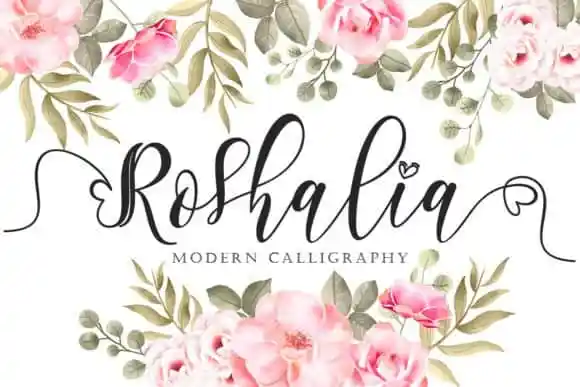
A fonte Roshalia Calligraphy é uma combinação única de elegância romântica com leveza casual. Ela surge do talento do designer yogaletter6, conhecido por criar tipos de escrita que se movem sobre o baseline num tom encantador e aconchegante. Esta fonte traz ligaturas e swashes que dão ao seu texto um toque delicado e sofisticado. Os caracteres dançam suavemente nas linhas de base, criando uma atmosfera envolvente e suave. Eles permitem que você acessione todos os seus gílios e swashes sem esforço algum graças à sua codificação PUA. A Roshalia Calligraphy é ideal para um leque diversificado de projetos gráficos, seja um cartão personalizado ou até mesmo uma bela capa de livros. Ela se destaca como uma fonte que transmite tanto romantismo quanto elegância no design do texto.